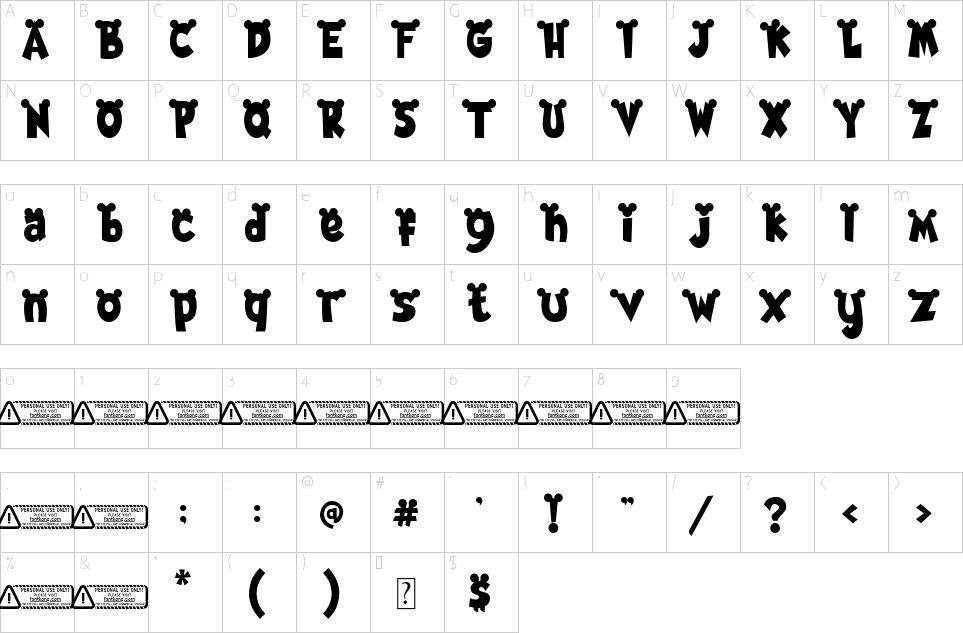
Aqui está uma descrição em português para a página de download da fonte ‘Minnie Font | 1001 Free Fonts’, seguindo as regras fornecidas: O Minnie Font é uma opção gratuita e divertida para aqueles que gostam de adicionar um toque de alegria às suas criações digitais. Desenvolvido pelo designer anônimo de fontes que criou essa fonte única e engraçada, o Minnie Font se destaca entre as muitas opções disponíveis. Com seu design encantador e colorido, é perfeito para criar textos alegres e divertidos para blogs, posts de redes sociais, e até mesmo para adicionar um toque de diversão nos aplicativos móveis. Este fonte, que tem sido baixado mais de mil e oitocentos e trinta vezes, é uma ótima maneira de explorar novas maneiras de personalizar seus projetos digitais. Adquira já a sua cópia do Minnie Font e faça seus projetos ficarem ainda mais alegres e divertidos.